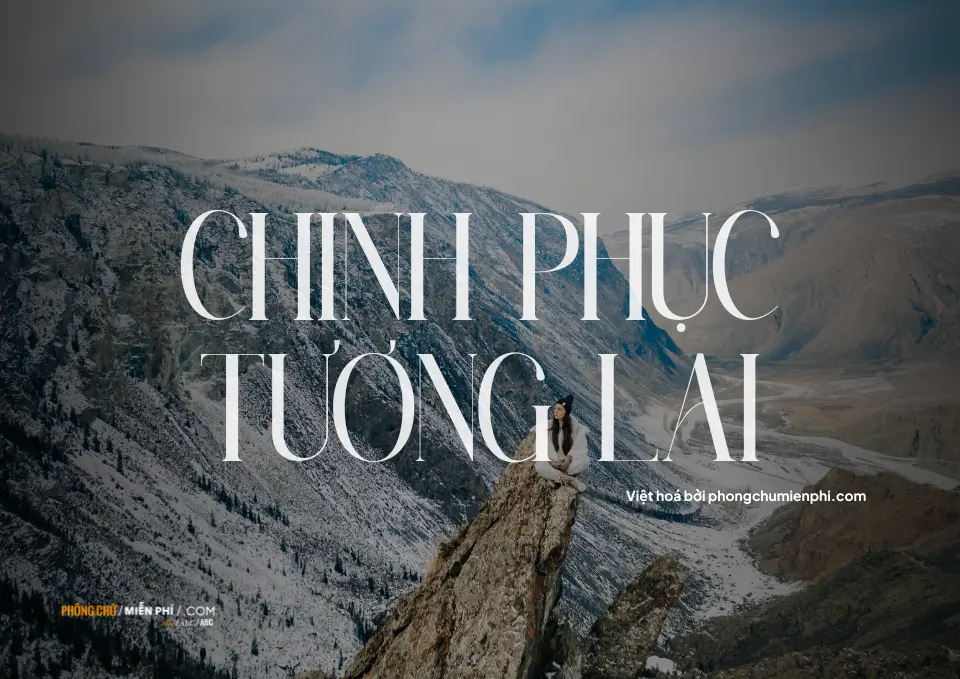
Font Việt hoá PCMP Showhan Vintage
Phông chữ PCMP Showhan Vintage là một phông chữ serif hiện đại và sang trọng, thể hiện vẻ đẹp vượt thời gian và sức hấp dẫn xa hoa. Với nét thẩm mỹ tinh tế và sự tinh tế, phông chữ này mang đến nét hoài cổ cho thiết kế của bạn. Rất phù hợp cho logo, tiêu đề, tiêu đề phụ và các hình thức trang trọng khác như thiệp mời, nhãn mác, logo, tạp chí, sách, thiệp chúc mừng/thiệp cưới, bao bì, thời trang, mỹ phẩm, văn phòng phẩm, tiểu thuyết, nhãn mác hoặc bất kỳ mục đích quảng cáo nào.
Showhan được xây dựng với các tính năng OpenType và bao gồm 100 chữ ghép, chữ thay thế, số, dấu câu, và cũng hỗ trợ các ngôn ngữ khác.
AC AD AL AN AR AS AT AU AV BE CA CE CH CO CT DE DI EA EC ED EE EL EM EN EP ER ES ET FE FO FR GE HA HE HI HO IE IC IL IN IO IR IS IT JU KE LA LE LI LL LO LY MA ME MI NC NE NG NO NT OC OF OM ON OO OP OR OT OW PA PR RA RD RE RI RO RS RT SE SH SI SO SS ST TA TE TH TI TO TR TT UM UN UR VE WI WO